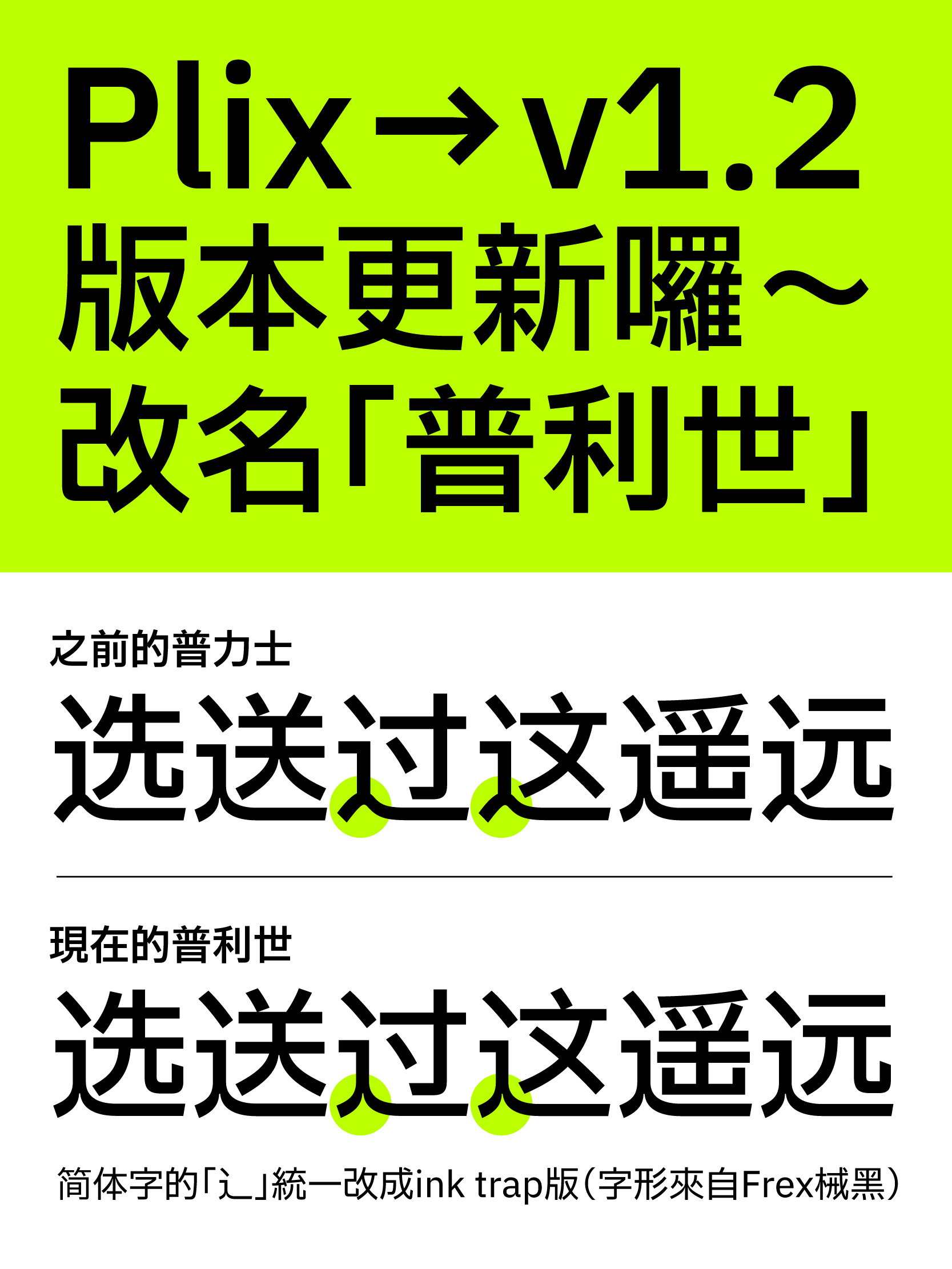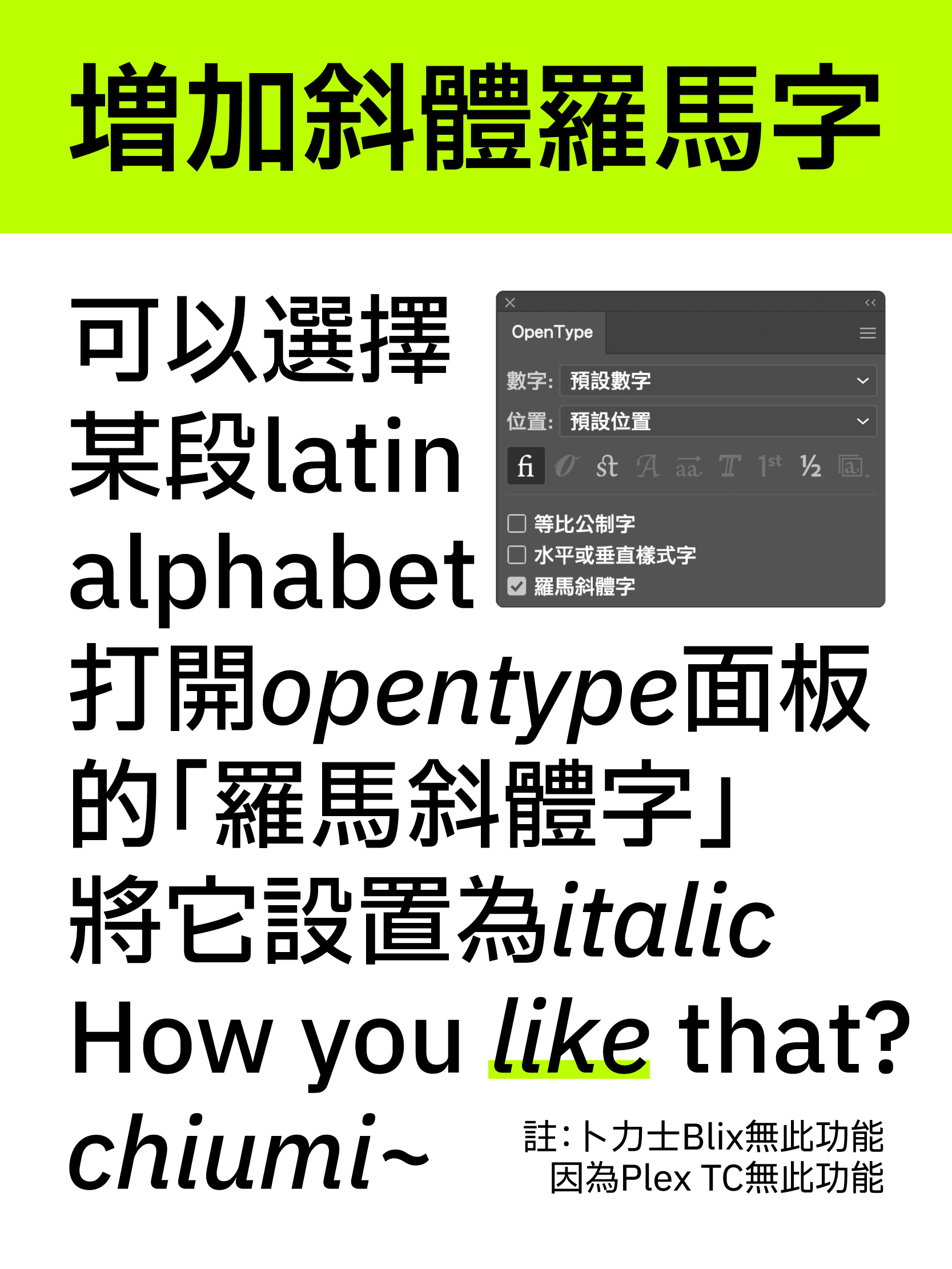
Plix
普利世(Plix)是一款基于 IBM Plex Sans 汉字系列深度优化而来的免费可商用中文黑体,在保留 IBM Plex Sans 人文主义无衬线设计理念的基础上,进一步融入机械感与现代工业美学,使字体兼具亲和力、科技感与高辨识度。字体提供 Plix(普利世)与 Blix(卜力士)两个版本,分别以日文字形(JP)和繁体字形(TC)为设计基础,兼容简体中文、繁体中文及日文排版需求。其中,Plix 采用日文字形与角落标点设计,整体风格更加硬朗利落;Blix 则采用繁中字形与居中标点,视觉更加柔和自然,可满足不同地区及设计风格的应用需求。
在字形设计上,普利世延续了 IBM Plex Sans 清晰理性的骨架结构,并针对大量中文字形进行了重新修整,优化笔画避让关系与字面比例,使整体视觉更加均衡统一。字体采用 Ink Trap(油墨陷阱)设计,在笔画交汇及转角位置加入细微的凹口结构,可有效降低印刷过程中油墨扩散带来的边缘模糊问题,尤其在小字号印刷场景下依然能够保持良好的清晰度与辨识度,同时也形成了具有现代工业气质的独特视觉特征。
最新发布的 v1.2 版本中,字体正式由「Plix」更名为「普利世」,并对简体中文字形进行了进一步优化,统一将「辶」部件调整为 Ink Trap 风格(字形参考 Frex 机黑),让整套字体在细节表现上更加协调一致。此外,新版本还新增了 Roman Italic(罗马斜体)OpenType 功能,在支持 OpenType 特性的设计软件中,可直接启用罗马斜体样式,使英文排版拥有更加自然的斜体效果,进一步提升中西文混合排版的专业性与设计表现力。
字体提供 Thin、ExtraLight、Light、Regular、Text、Medium、SemiBold、Bold 共 8 种字重,能够满足从正文阅读到品牌标题、海报设计、UI 界面、包装视觉、科技产品、游戏界面等多种设计场景。现代、理性且富有未来感的字形风格,使普利世不仅具备优秀的阅读体验,也拥有鲜明的品牌识别度,是一款兼具实用性与设计感的免费商用中文黑体。
总体来看,普利世是一款兼具现代工业感与人文气质的免费商用中文黑体,在 IBM Plex Sans 的优秀骨架基础上进行了大量本地化优化,不仅加入 Ink Trap 设计提升了印刷与小字号显示效果,还通过多字重、Roman Italic 斜体及持续迭代的字形优化,大幅增强了中西文混排能力与实际应用价值。无论是品牌视觉、科技产品、UI 界面、海报设计还是数字媒体排版,普利世都能够提供稳定且富有辨识度的视觉表现,是一款兼顾设计品质、专业排版与免费商用授权的高质量中文黑体字体。